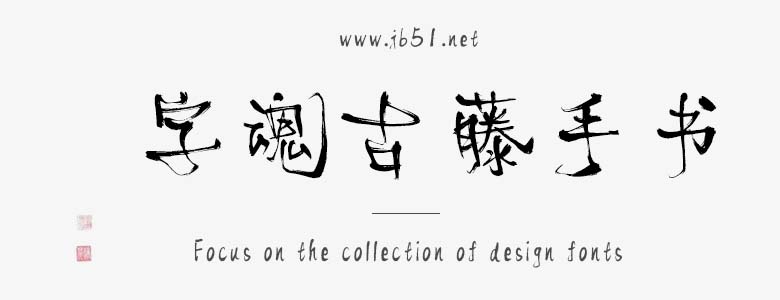
字魂古藤手書字體是由字魂字庫推出的毛筆書法字體,該字體包含9503個中文、字母、 符號和數(shù)字,具有中國風的風格,適合應用于藝術設計、平面宣傳設計、網頁設計,書法字帖等領域。
字魂古藤手書字體是一款商用的硬筆手寫,毛筆書法,創(chuàng)意字體,該字體包含9503個中文、字母、 符號和數(shù)字,具有中國風的風格,可以滿足您設計上的各種需求,該字體主要用于企業(yè)文化等場景, 您不但可以在字魂網下載字魂古藤手書字體,同時還有眾多毛筆書法字體、創(chuàng)意字體等可供選擇!